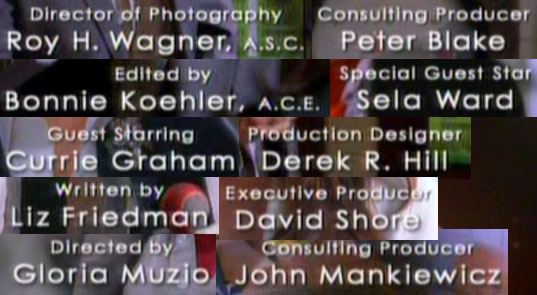
Schrift in »Dr. House«
Ich bin begeisterter Seher von Dr. House (wird auf RTL und SF zwei ausgestrahlt) und frage mich schon länger, wie die verwendete Schrift für Vorspann und Credits heißt.
Hier Ausschnitte aus dem Vorpann:
Und hier aus den Credits:
Unterscheiden sich diese zwei Schrift? Oder ist das jeweils ein anderer Schnitt der selben Schriftart?
die Schrift die sie in deinem Vorspann (und Abspann) verwenden ist die Futura.
Der Unterschied: Im Vorspann kommen (fast) nur Großbuchstaben vor. Es könnte natürlich ein anderes Gewicht verwendet worden sein. Das lässt sich aber dank Fernsehtechnik, Schatten hinter der Schrift, etc. oft nicht so genau bestimmen.
Ich glaub Du hast recht, aber nur mit der Century G. Hässlich ist das ganz und gar nicht. Höchstens weil die Schnipsel unten in der Grafik alle so zusammengepappt sind, aber in der Grafik oben sieht das doch schon ganz anders aus.